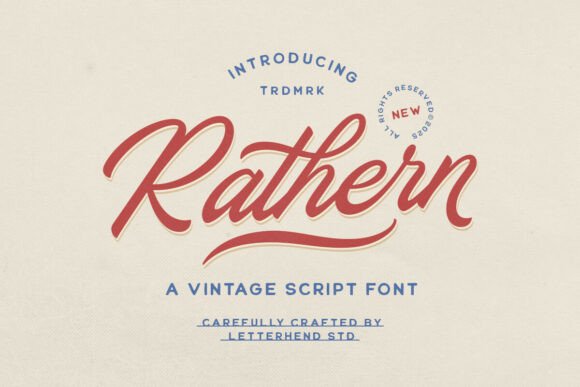
Rathern Vintage Script
適切なデザイン要素を見つけるのは難しい場合がありますが、Rathern Vintage Scriptは作品を即座に引き立てる優れたコレクションを提供します。
POD(オンデマンド印刷)製品、結婚式の招待状、またはソーシャルメディアのグラフィックを作成している場合でも、Rathern Vintage Scriptは理想的です。